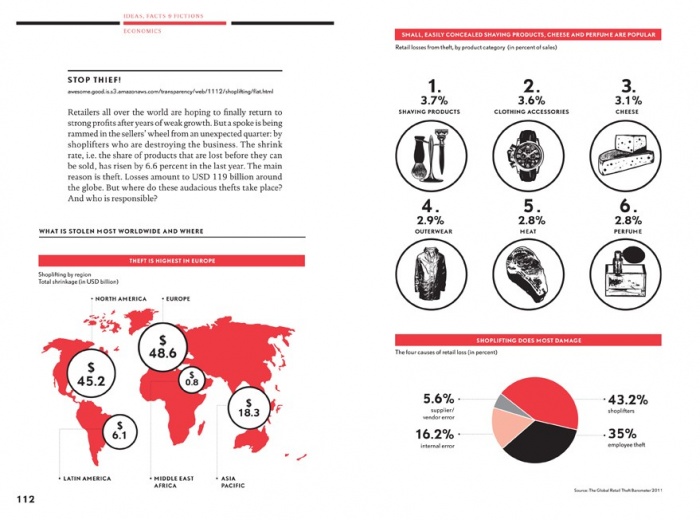
Fließtext-Schrift
ich bin auf der Suche nach einer serifenbetonten Schrift für einen Fließtext. Die Headline ist in einer Avenir Condensed Bold gesetzt. Im Moment benutzte ich die Sabon Regular. Sie wirkt jedoch eher altertümlich als modern, ist aber besser lesbar als andere Schriften, die ich bis jetzt ausprobiert habe, darunter Slab Schriften wie die Caecilia.
Die Anmutung sollte wie im hochgeladenen Beispiel sein. Vllt könnt ihr mir behilflich sein?
Die Beurteilung von Lesbarkeit ist ja immer so eine Sache. Zur Avenir könnte man sich mal die geometrische Slab Hypatia ansehen. Formal passend fände ich auch Henriette oder Ingeborg.
Etwas kerniger und frischer als die Sabon kommen unter den Antiquas beispielsweise die FF Dora, FF Tisa, Premiéra oder Skolar daher.
Beides wahrscheinlich eine Frage der Interpretation:
1) Dem Namen nach ist es eine Sans, das stimmt. Aber ein Sans hat gar keine Serifen. Die Hypatia hingegen hat welche und die kommen am ehesten einer Slab Serif nahe.
2) Ja, bzgl. Gesamtanmutung wirkt die Hypatia eher humanistisch. Schaut man sich aber die »Einzelformen« an, wird man ein geometrisches Konstruktionsprinzip feststellen. Das klingt auch im Beschreibungstext an:
Phinney hatte schnell eine konkrete Vorstellung des Eindrucks, den die Schrift machen sollte. Die Großbuchstaben sollten (wie Trajan®*) klassisch-römische Proportionen haben, während für die Kleinbuchstaben zur Verbesserung von Erscheinungsbild und Lesbarkeit klare geometrische Formen vorgesehen waren. Obwohl Hypatia Sans ursprünglich für Überschriften zwischen 18 und 36 Punkt Größe erdacht wurde, kann die Schrift aufgrund ihrer guten Lesbarkeit auch für Fließtext im Bereich von 10-12 Punkt verwendet werden. Angedeutete gewinkelte Serifen im linken oberen Bereich der Zeichen bilden einen modernen Kontrapunkt zu einem Design, das ansonsten im Stil der 1920er oder 1930er Jahre gehalten ist.
Beim Design von Hypatia Sans konzentrierte Phinney sich auch auf die Beziehung zwischen Einsetzbarkeit und Stil bei vorhandenen geometrischen Schriften. Beides sind wünschenswerte Eigenschaften, aber die Ausprägung jeder einzelnen davon schien jeweils die Obergrenze für die andere darzustellen. Phinney suchte also beim Design von Hypatia Sans nach einem Optimum, bei dem sowohl Einsetzbarkeit als auch Stil so groß wie möglich sein sollten.
Warum nicht bei der DTL Documenta bleiben?
Reichen die Andeutungen von Serifen (ich hielte es eher für Anstriche) bei bdhjklmnpruцчшщю und J (nur so als schneller Überblick) für die Definition oder einer Anmutung einer Slab?
Wie gesagt, das ist meine Interpretation. Man könnte vielleicht auch »Hybrid« oder »Semi Sans« oder »Semi Serif« oder … dazu sagen. Mit »Sans« tue ich mich persönlich schwer. Aber da gibt es sicher wichtigere Themen.